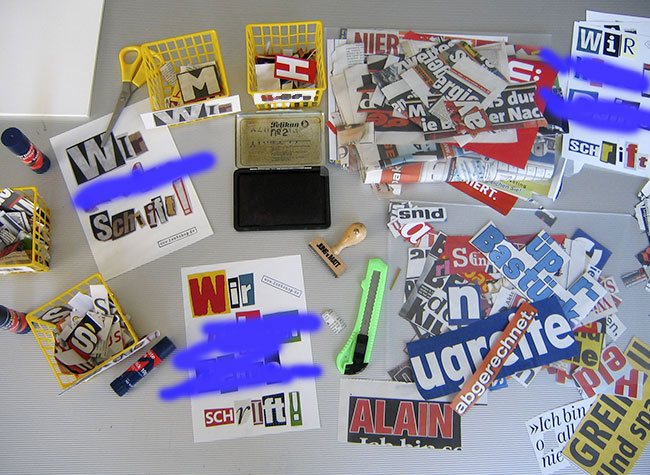
Noch wenige Stunden ...... bis zum angekündigten Ereignis auf der Frankfurter Buchmesse.
Inzwischen liegt uns das Foto eines konspirativen Arbeitsplatzes vor. Leider
wurden entscheidende Hinweise mittels Spraydose unkenntlich gemacht. Was wir
sehen sind geklebte Buchstaben, wie man sie von Erpresserbriefen her kennt ..
eine Wir-Botschaft ist zu entziffern, deren Aussage sich nicht dechiffrieren
![]() Dieses Foto erreichte FontShop heute per E-Mail. Es zeigt offensichtlich
einen konspirativen Arbeitsplatz, an dem – in einer Art Serienproduktion
– kriminelle Botschaften verfasst werden. Die Botschaft wurde unkenntlich
gemacht. Im Bodytext der E-Mail hieß es nur: »... morgen, auf der
Buchmesse!!!« Was kommt da auf uns zu? Wir sind
ratlos.